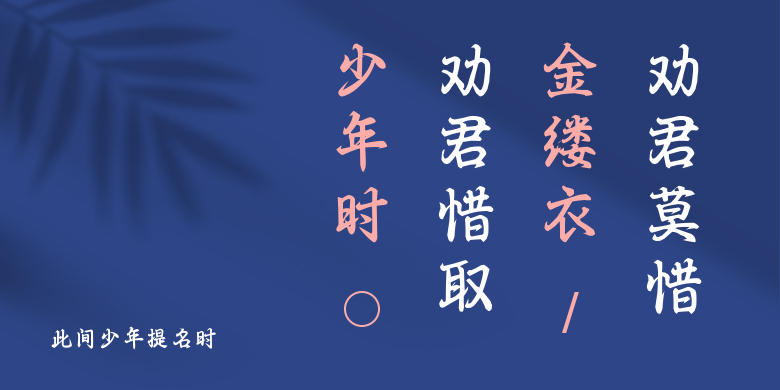
此间少年提名时
此间少年提名时,这款字体结构工整、笔画清晰,兼顾美观与易读性,适用于标题、正文、海报、包装、LOGO 等多种场景。字形优雅稳定,风格百搭耐看,适配日常排版与创意设计,让文字呈现更舒适、更具质感。此间少年提名时一笔一画,皆是细节,以均衡的比例、流畅的线条打造舒适视觉体验,字形端正大气,风格简约现代。无论是商业设计、品牌宣传还是日常排版,都能轻松驾驭,让文字更有格调与力量。此间少年提名时字体下载。